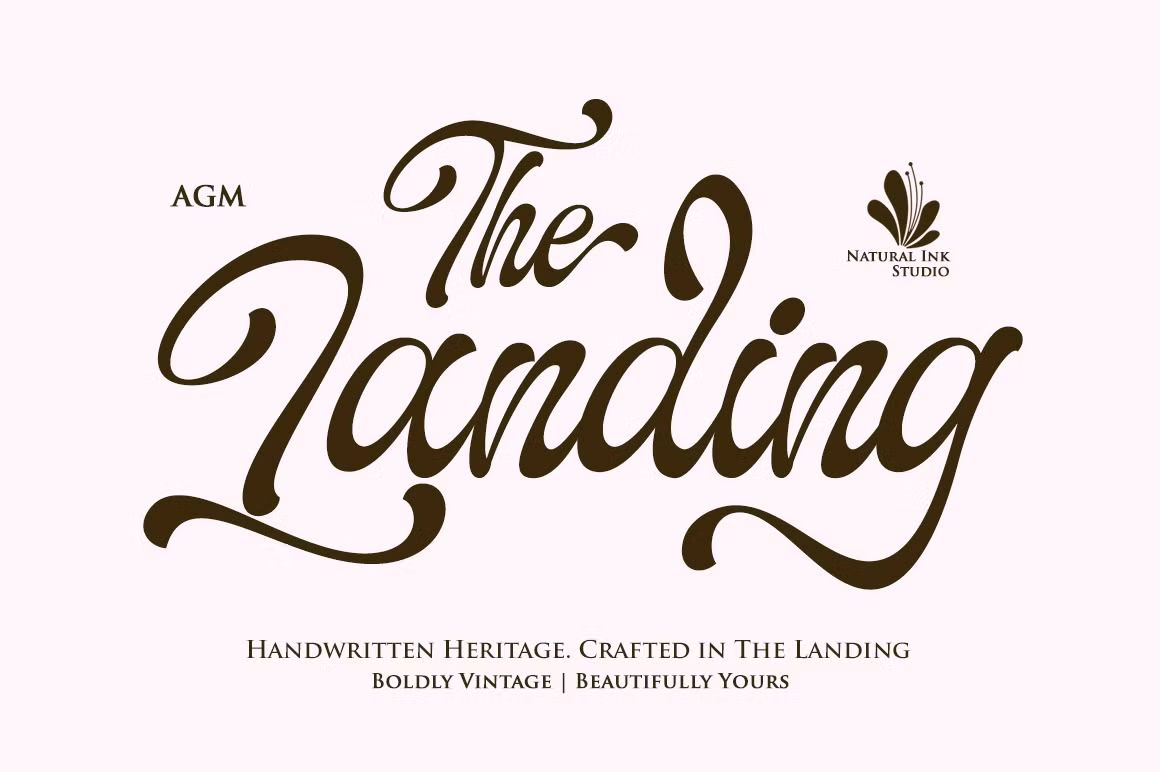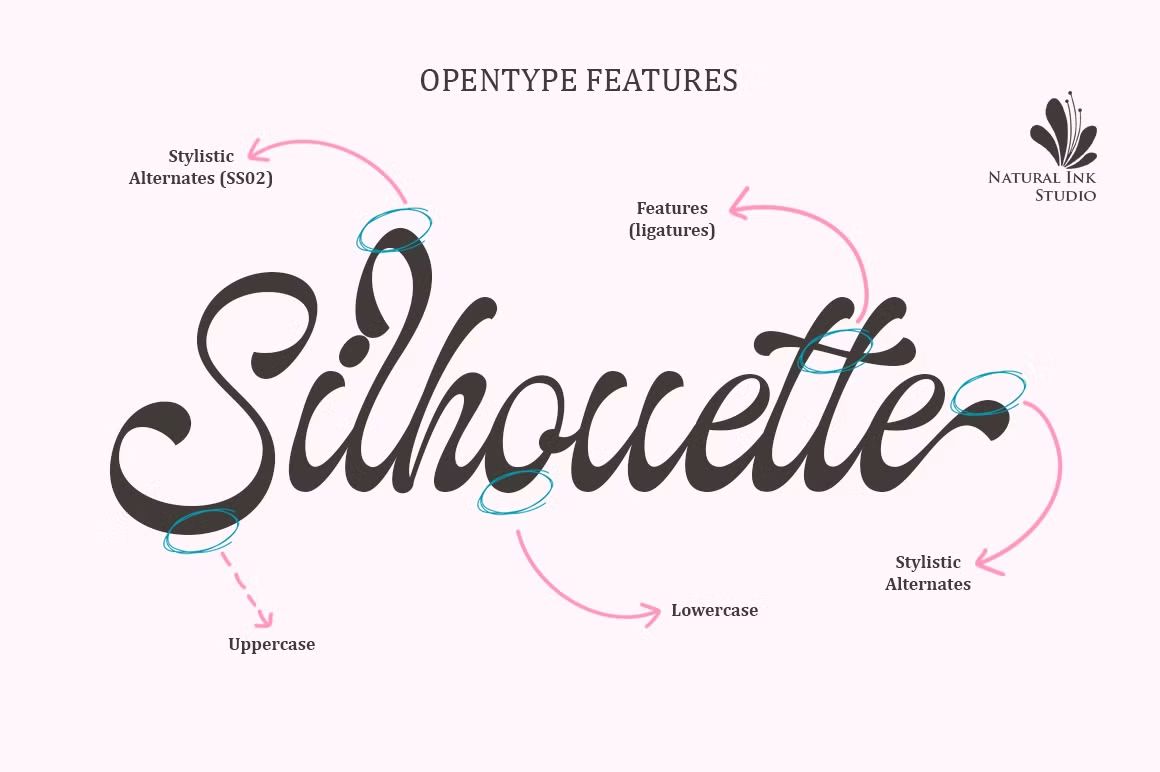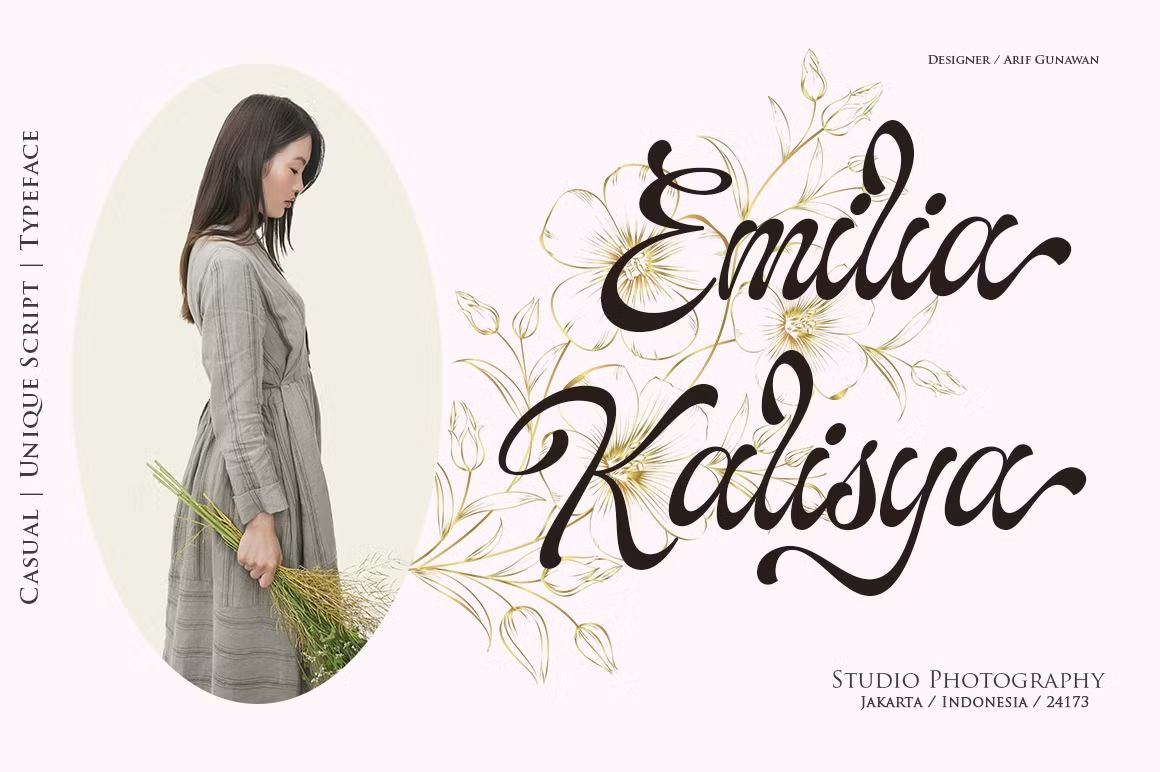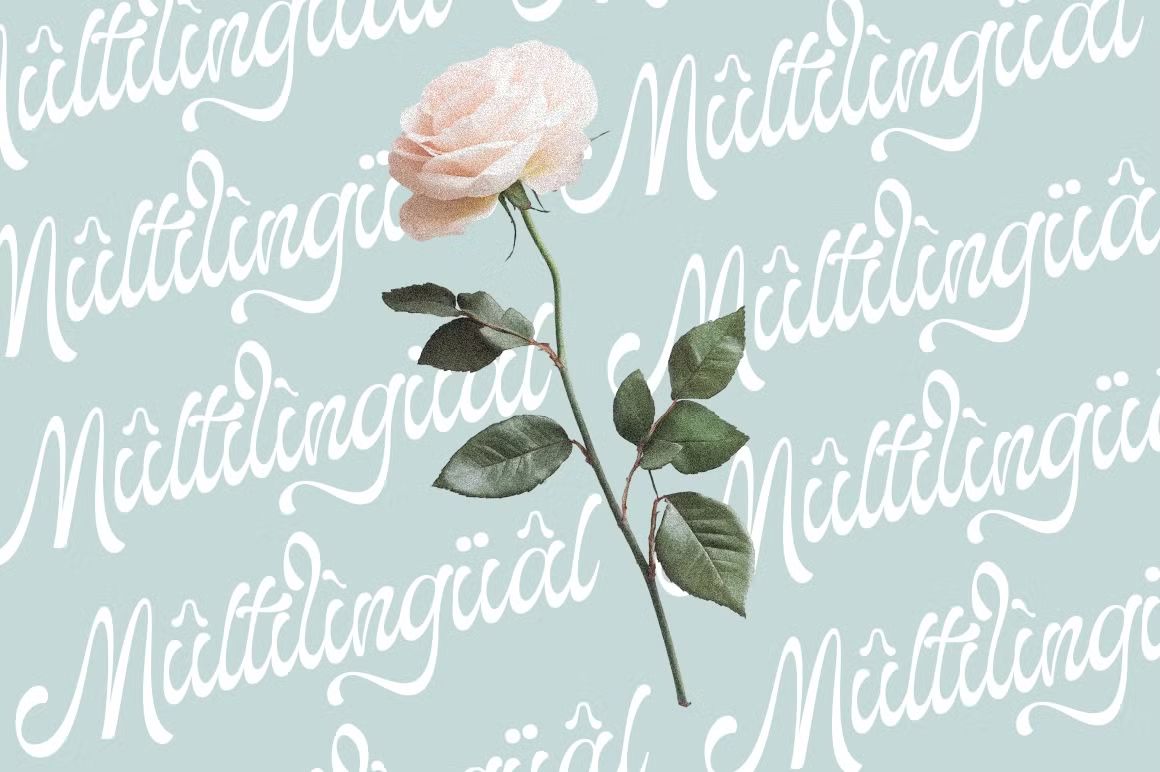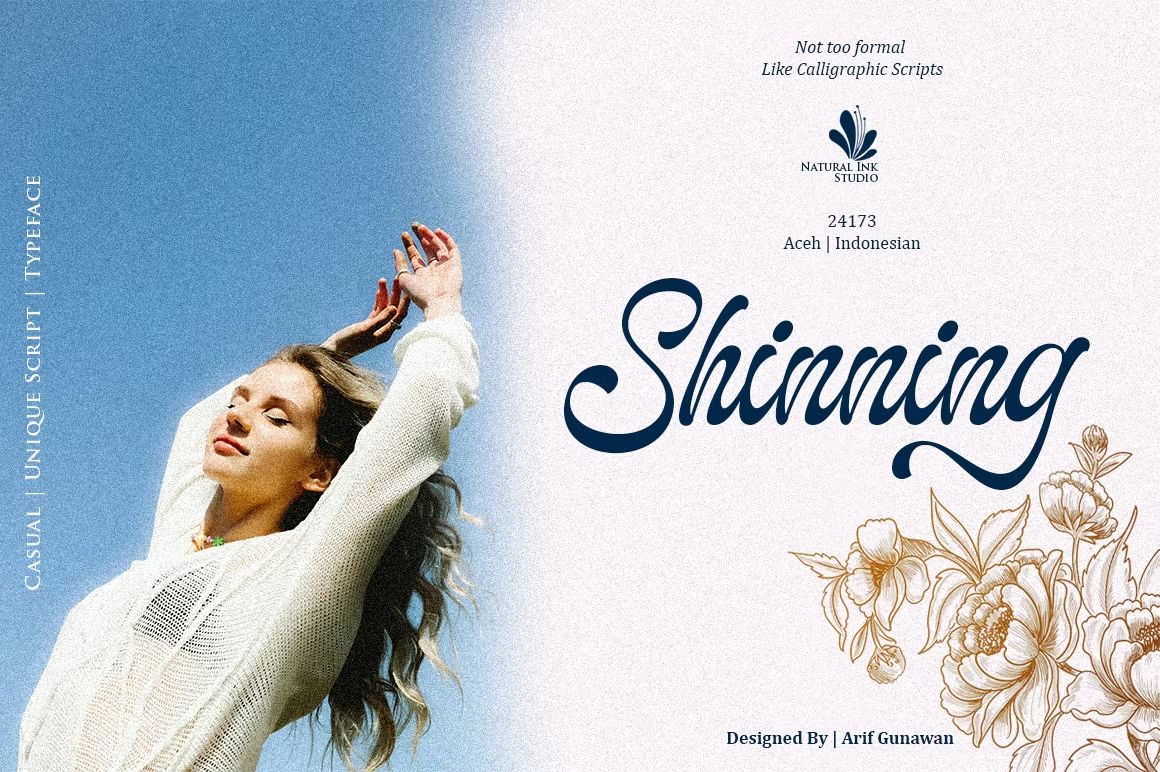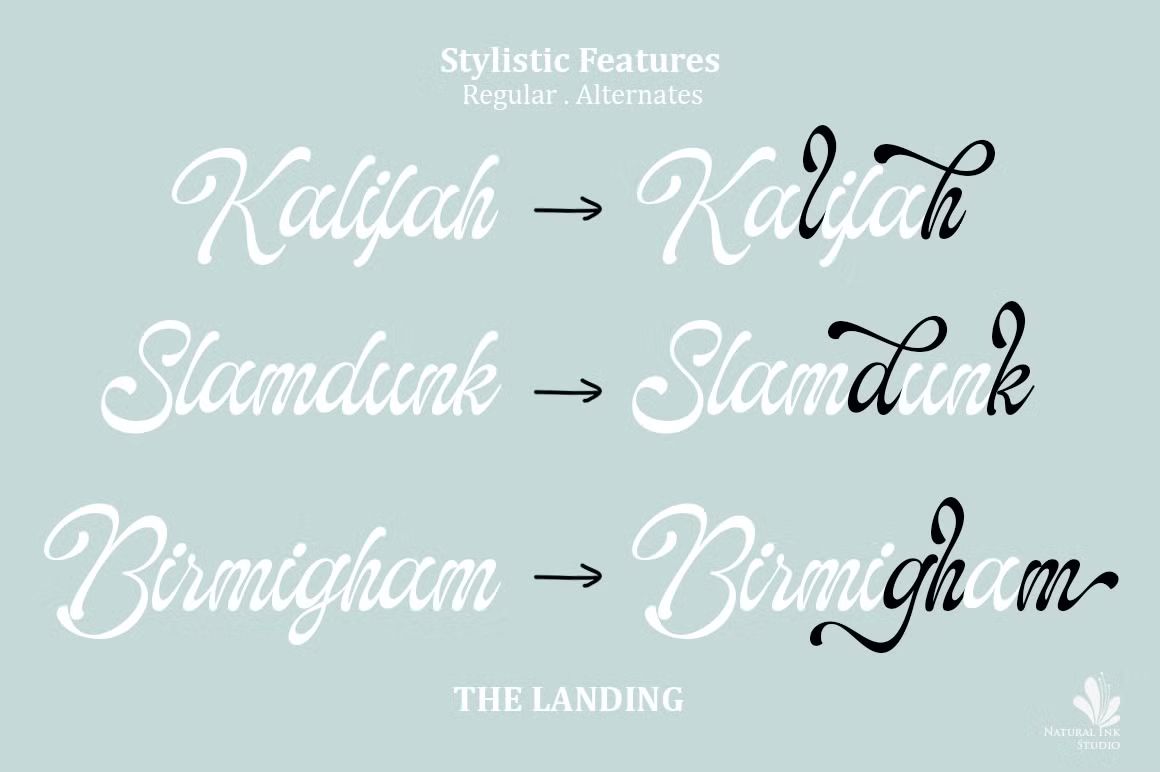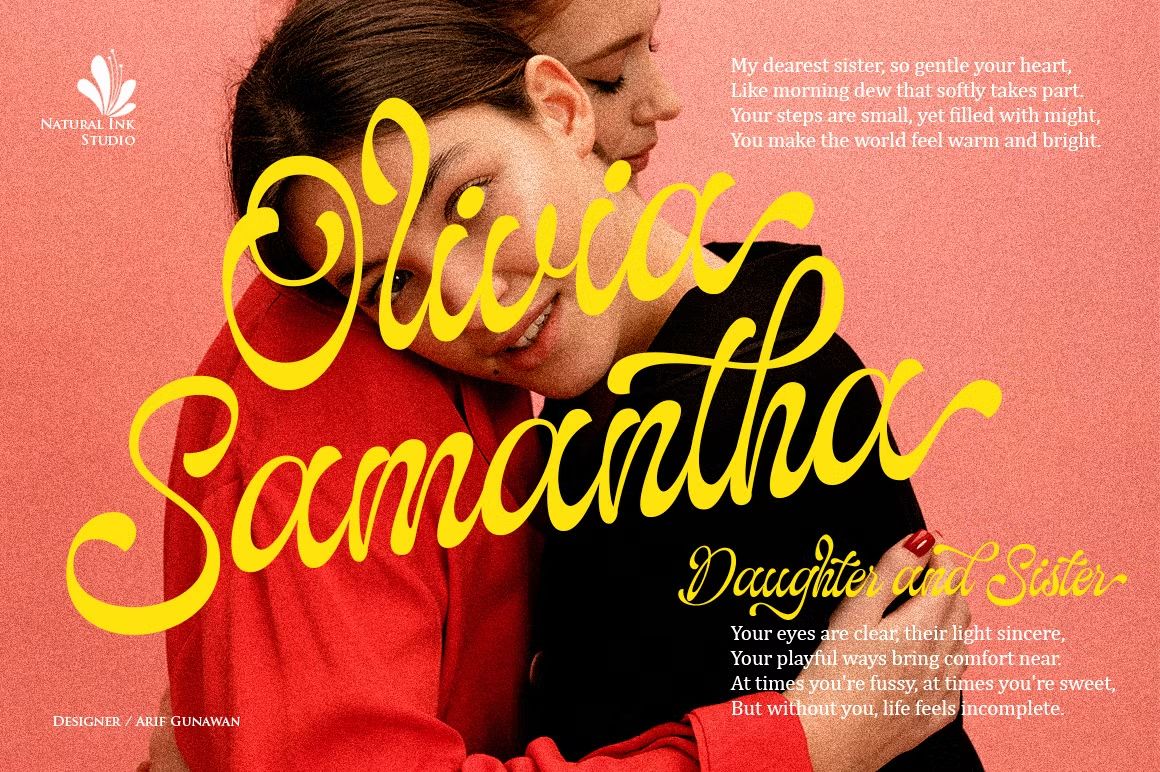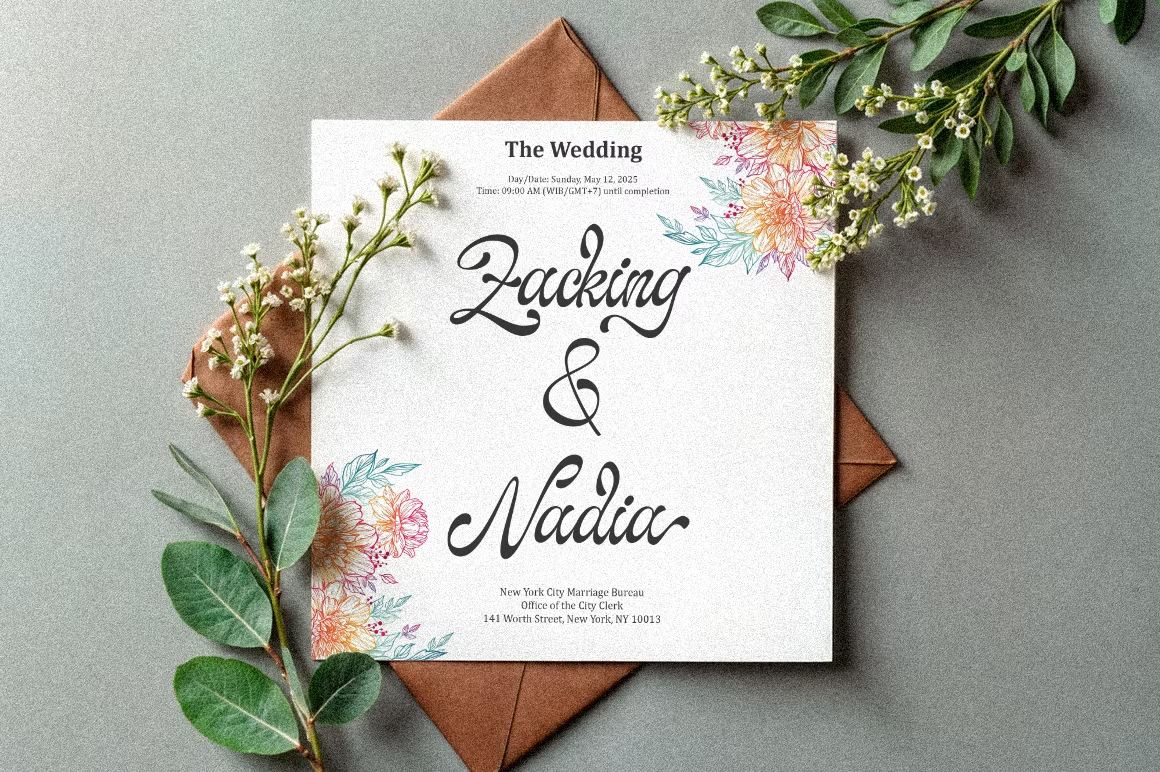
The Landing – Script Font
The Landing adalah font script bergaya tulisan tangan yang halus dan elegan, dengan alur yang mengalir dan karakter yang lembut. Didesain untuk menyampaikan kesan romantis dan personal, font ini ideal digunakan untuk undangan pernikahan, logo feminin, kutipan estetik, kartu ucapan, dan konten media sosial. Cocok untuk berbagai proyek yang mengutamakan sentuhan artistik dan emosional.
• Gaya tulisan tangan yang anggun dan mengalir
• Ideal untuk wedding, branding, dan desain romantis
• Termasuk huruf besar, kecil, angka, simbol, dan ligatur